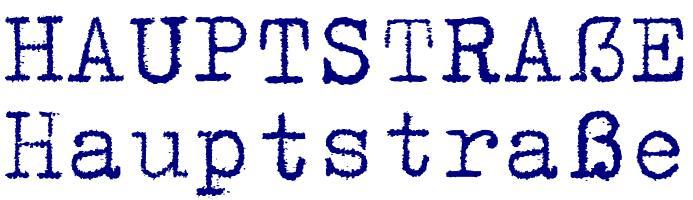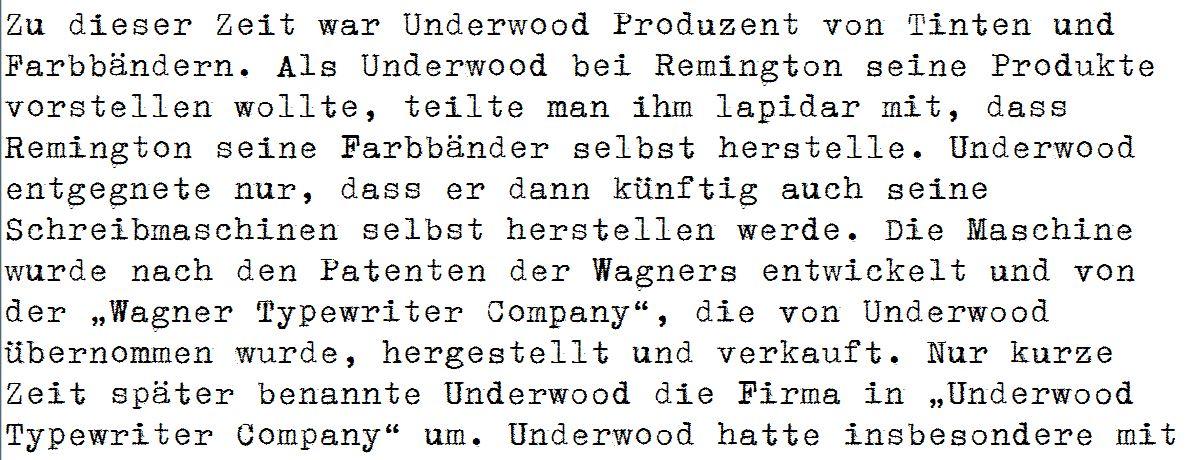
[Mitglied catf…] Geschrieben Juli 17, 2016 Teilen Geschrieben Juli 17, 2016 Vor längerer Zeit hatte ich mal irgendwo eine Anleitung gesehen, wie man so einwe Pseudo-Zufällige Glyphentausch-Geschichte per OpenType-Features huinbekommt, damit innerhalb eines Textes ein sich wiederholender Buchstabe aus einem Soretiment quasi im Kreis tauscht Und das eben so fr alle Buchstaben des Alfabets, eben in der Anzahl der Nutzung. Also für das "STERNL" bräuchte ich mehr Alternativformen, als für Q,Y, X und weiterer eher seltene Buchstaben, die dann nicht unbedigt getauscht werden mssten. Ich habe nun gestern im Interenet nach einer Anleitung gesucht, aber eben leider nur gefunden, wie man die zusätzlichen Buchstabwen im Font unterbringt, was ja für mich gar nicht die Frage ist, gehts dann ins Eingemachte, wird es aber leider ziemlich vage bei den Beschreibungen, als sei dies patentrechtlich geschtzte Alien-Technologie. Ich habe nämlich nicht wirklich lust, hier das Rad noch mal selbst zu erfinden. Daher hoffe ich, dass jemand hier mir einen Tipp geben könnte Nur um zu zeigen, worauf es hinaus laufen soll, hier vobn Hand bei H, T und t Link zu diesem Kommentar
[Mitglied 92ad…] Geschrieben Juli 17, 2016 Teilen Geschrieben Juli 17, 2016 Sie meinen, wie bei dem Font, der die Handschrift von Sigmund Freud simuliert? Link zu diesem Kommentar
Ralf Herrmann Geschrieben Juli 17, 2016 Teilen Geschrieben Juli 17, 2016 Hier werden die gängigen Methoden mit Beispielcodes erklärt: (Bis Randomization runterscrollen) http://opentypecookbook.com/common-techniques.html Link zu diesem Kommentar
[Mitglied catf…] Geschrieben Juli 17, 2016 Themen-Ersteller Teilen Geschrieben Juli 17, 2016 Danke! Genau die Seite hatte ich gemeint, aber irgendwie nicht wiedergefunden. Gleich mal angewendet, klappt schon mal gut, auch wenn ich derzeit nur 3 alternativen der Buchstaben drin hab, und da keine verschiedene Anzahl an Alternativglyphen vorgesehen ist, die ich halt gern so zu sagen "nach Gießzettel" gemacht hätte. Das ist da schon mal ein Blick drauf. Ich weiß, bei Typenhebelmaschinen gehen weder typografische Anführungsstriche noch ẞ - aber warum nicht??? 3 Link zu diesem Kommentar
[Mitglied Mart…] Geschrieben Juli 17, 2016 Teilen Geschrieben Juli 17, 2016 Warum sollten bei der Schreibmschinenschrift Buchstaben unterschiedlich hoch stehen, wenn der Wagen gar nicht in der Höhe bewegt wird? Das wäre, als ob man Merkmale der Unechtheit einbaut, besonders gut sichtbar, wenn zwei gleiche Buchstaben nebeneinander unterschiedlich hoch stehen. Das ist mit der Schreibmaschine absichtslos nicht möglich. Link zu diesem Kommentar
[Mitglied 92ad…] Geschrieben Juli 17, 2016 Teilen Geschrieben Juli 17, 2016 vor 1 Minute schrieb Martin Z. Schröder: Warum sollten bei der Schreibmschinenschrift Buchstaben unterschiedlich hoch stehen, wenn der Wagen gar nicht in der Höhe bewegt wird? Das wäre, als ob man Merkmale der Unechtheit einbaut, besonders gut sichtbar, wenn zwei gleiche Buchstaben nebeneinander unterschiedlich hoch stehen. Das ist mit der Schreibmaschine absichtslos nicht möglich. Richtig. Daher oben auch mein Hinweis auf Harald Geisler und seine Sigmund Freud Typeface. Warum ausgerechnet bei Maschinschrift etwas einbauen, was nur bei Handschrift oder allenfalls bei Handsatz vorkommt? Link zu diesem Kommentar
[Mitglied catf…] Geschrieben Juli 17, 2016 Themen-Ersteller Teilen Geschrieben Juli 17, 2016 Doch, wenn die Bohrungen der Typenhebel in ihren Gelenken etwas abgenutzt sind, Zudem sind die auch ohne Abnutzung schon mit ein wenig Spiel eingebaut, um eben so leichtgängig wie möglich zu sein. Zusätzlich wird bei Großbuchstaben je entweder das Segment abgesenkt, bzw der Wagen gehoben, und auch das erfolgt nicht immer mit absoluter Präzision, das es hier es auch zu mehr tänzelnden Buchstaben kommt. Link zu diesem Kommentar
[Mitglied Norb…] Geschrieben Juli 17, 2016 Teilen Geschrieben Juli 17, 2016 Ich hab als Kind ziemlich oft mit der alten Typenhebelmaschine meines Vaters ’rumgespielt (z. B."Bitmap"-Bilder getippt, nur hieß das damals noch nicht so) und auch später noch Schülerzeitungsseiten geschrieben, daher kann ich bestätigen, dass das mit den unterschiedlichen Höhen häufig vorkam, meist war es auch abhängig davon, mit wie viel Kraft man anschlug. Und der Wagen wurde ja bei jedem Großbuchstaben angehoben (engl: to shift) ... wenn dann der nächste Buchstabe anschlug, bevor der Wagen wieder richtig unten war, gab's manchmal seeehr interessante Bilder. Link zu diesem Kommentar
[Mitglied Mart…] Geschrieben Juli 17, 2016 Teilen Geschrieben Juli 17, 2016 Nach dem Umschalten von Groß- auf Kleinbuchstaben können letztere zu tief stehen, sogar wesentlich. Das hängt vom Schreiber ab, und es wird sicherlich nur bestimmte Buchstaben treffen. Daß zwei nebeneinanderstehende Kleinbuchstaben unterschiedlich hoch stehen, ist fast ausgeschlossen, aber daß der zweite schwächer ist als der erste, kommt bei schnellem Doppelanschlag durchaus vor. Andersherum eher nicht, also erst schwach und dann stark wird wohl nicht vorkommen beim Schreiben auf der Schreibmaschine. Diese Fehler müßten sich allerdings wiederholen. Man kann sich im Netz genug Fotos von Schreibmaschinenseiten anschauen und wird finden, daß Dokumente in sich immer dieselben Fehler zeigen, weil die Schreiber dieselben Fehler machen. Es gibt auch Fehler, die nicht vermieden werden können wie schiefe Buchstaben durch verbogene Typenhebel oder stets etwas zu hoch oder zu tief stehende oder immer gleich unsaubere Anschläge durch fehlerhafte Typen. Bei manchen Maschinen wird der Wagen gehoben, bei anderen das Typenfeld abgesenkt. Das macht man nur, wenn man entweder Großbuchstaben oder bestimmte Satzzeichen schreibt. Bei fortlaufender Kleinschreibung oder festgestellter Großschreibung gibt es diese horizontale Bewegung nicht. Ein zufälliger Wechsel von Buchstaben entspricht nicht dem Maschinenprinzip, würde ich meinen. Ich habe an Schreibmaschinen nicht nur als Kind gespielt, sondern die ersten Jahre meines Journalistendaseins mein Geld darauf verdient (und habe auch noch drei Maschinen). Link zu diesem Kommentar
[Mitglied Plae…] Geschrieben Juli 17, 2016 Teilen Geschrieben Juli 17, 2016 Und bei Catfonts ist seine Rechtschreibung auch schon sehr abgenutzt. Du meine Güte: Wann liest Du mal Dein Posting vor dem Abschicken durch? Und jeder schaut zu und findet das scheinbar in Ordnung. Und das in einem Typografie-Forum. Ich fass es langsam nicht mehr. Link zu diesem Kommentar
[Mitglied catf…] Geschrieben Juli 17, 2016 Themen-Ersteller Teilen Geschrieben Juli 17, 2016 Sorry, man soll eben besser nicht schreiben UND Telefonieren ... Link zu diesem Kommentar
[Mitglied Diet…] Geschrieben Juli 17, 2016 Teilen Geschrieben Juli 17, 2016 vor 2 Stunden schrieb Plaeus: scheinbar Auch wenn sogar Arno Schmidt öfter mal »scheinbar« geschrieben hat, wo »anscheinend« gemeint war: Wenn hier schon die Rechtschreibung beanstandet wird, scheint es mir nicht verkehrt, auch auf diesen Bedeutungsunterschied aufmerksam zu machen. 3 Link zu diesem Kommentar
[Mitglied Erwi…] Geschrieben Juli 18, 2016 Teilen Geschrieben Juli 18, 2016 vor 12 Stunden schrieb Plaeus: Und jeder schaut zu und findet das scheinbar in Ordnung. Und das in einem Typografie-Forum. Ich fass es langsam nicht mehr. Das merken wir schon. Wir merken aber auch, dass Catfonts sehr viele Beiträge verfasst, im Eilzugstempo Schriften erstellt, diese mitunter kostenlos zur Verfügung stellt, den meisten die bei ihren Schriften oder Reinzeichnungen nach Hilfe rufen Unterstützung anbietet usw. … 11 Link zu diesem Kommentar